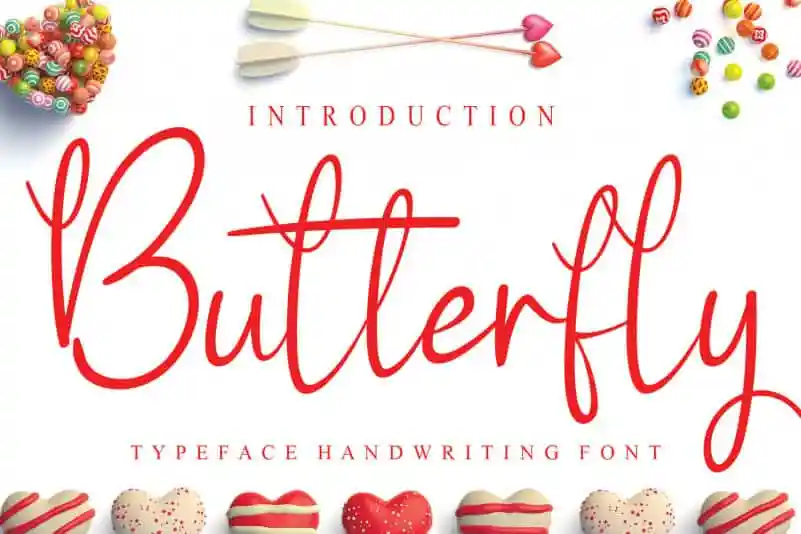
Butterfly1 Script Font – Download Grátis
A Butterfly1 Script Font é uma escolha perfeita para quem busca uma fonte escrita a mão que transmite emoção e elegância ao mesmo tempo. Essa fonte, criada pelo designer creativeletter, oferece um toque suave e natural à qualquer projeto em que você a use. Seja ele um cartão de aniversário delicado ou um layout editorial sofisticado, Butterfly1 Script Font trará uma atmosfera envolvente e autêntica a sua produção. Com linhas fluidas e detalhes sutis, esta fonte escrita a mão permite que você personalize seu design sem perder a essência única. Perfeita para aqueles desejos de um toque personalizado em seus materiais impressos ou digitais, ela é ideal para designers gráficos buscando adicionar um toque autêntico aos seus trabalhos. Seja você criando cartões de visita, fazendo revistas ou até mesmo decorando sua casa com itens pessoais – a Butterfly1 Script Font trará o charme de uma fonte escrita a mão ao seu projeto.